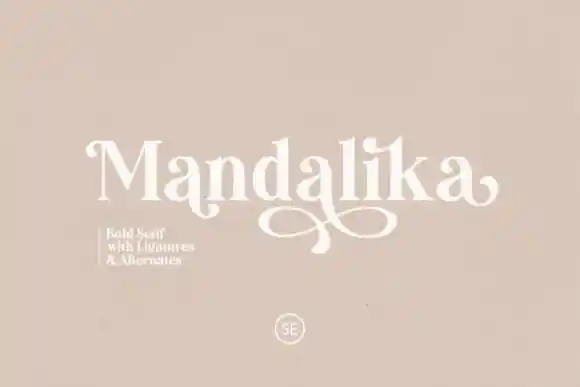
Mandalika Serif Font – Download Grátis
A Mandalika Serif Font é uma elegante escolha para designers que buscam sofisticação em suas criações digitais. Ela combina detalhes refinados com alternativas únicas, criando linhas fluidas e conectadas entre letras, ideal para impressões e logomarcas deslumbrantes. Essa fonte foi desenvolvida pelo font designer Saridezra, conhecido por sua habilidade em criar personalidades distintas para cada tipo de letra. A Mandalika apresenta uma coleção diversificada de ligaturas e alternativas, tornando-a ainda mais atraente e diferenciada. Outra característica marcante é o suporte ao multi-linguagem, oferecendo flexibilidade em diferentes plataformas e idiomas. Além disso, a fonte já foi puro assinatura (PUA) codificada, permitindo uma fácil integração em projetos de design complexos. Para quem busca uma fonte que não apenas se destaca visualmente, mas também oferece conforto para o olho e facilidade na leitura, a Mandalika Serif é definitivamente um item a ser considerado no seu próximo projeto de design.